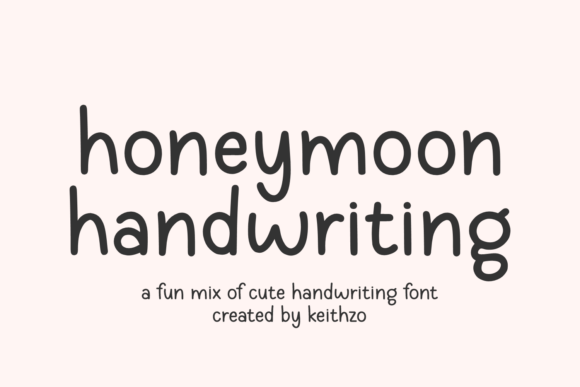
Honeymoon Handwriting
適切なデザイン要素を見つけるのは難しい場合がありますが、Honeymoon Handwritingは作品を即座に引き立てる優れたコレクションを提供します。
精密に作られたHoneymoon Handwritingは、クリーンなベクター、滑らかなタイポグラフィ、そして安心のための商用ライセンスを提供します。
POD(オンデマンド印刷)製品、結婚式の招待状、またはソーシャルメディアのグラフィックを作成している場合でも、Honeymoon Handwritingは理想的です。